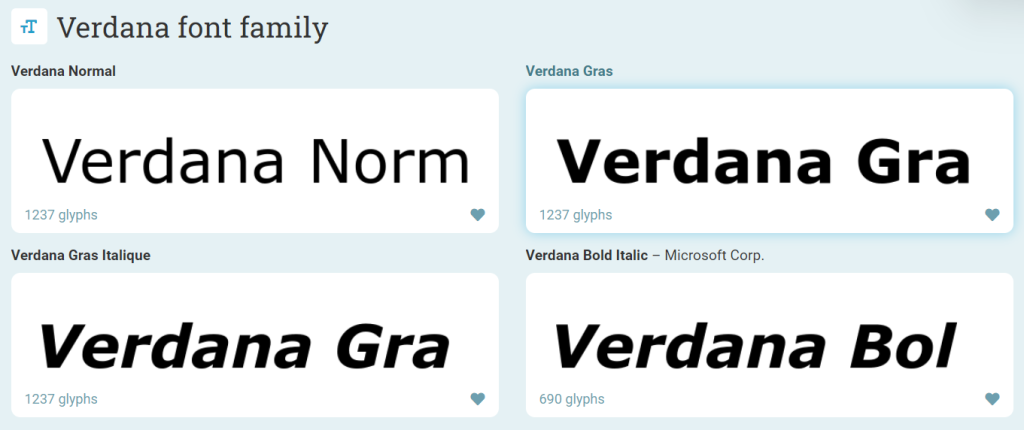
Verdana Bold Font
Tác giả: Matthew Carter
Ngày phát hành: 1996
Phân loại: Đơn Giản
Độ dày: Bold
Verdana Bold Font là một lựa chọn kinh điển và đáng tin cậy trong thiết kế đồ họa, được biết đến với độ rõ nét và khả năng đọc cao. Với các đường nét đậm và tròn trịa, font chữ không chân này tạo nên một vẻ ngoài hiện đại và chuyên nghiệp. Verdana Bold Font thường được sử dụng trong các thiết kế giao diện người dùng, tài liệu kỹ thuật và các ấn phẩm cần đảm bảo tính dễ đọc. Sự kết hợp giữa độ đậm nét và kiểu chữ sans-serif giúp Verdana Bold Font trở nên nổi bật và thu hút sự chú ý của người xem, đồng thời vẫn giữ được tính dễ đọc ngay cả ở kích thước nhỏ. Font chữ này là một công cụ thiết kế đa năng, phù hợp với nhiều loại dự án khác nhau.